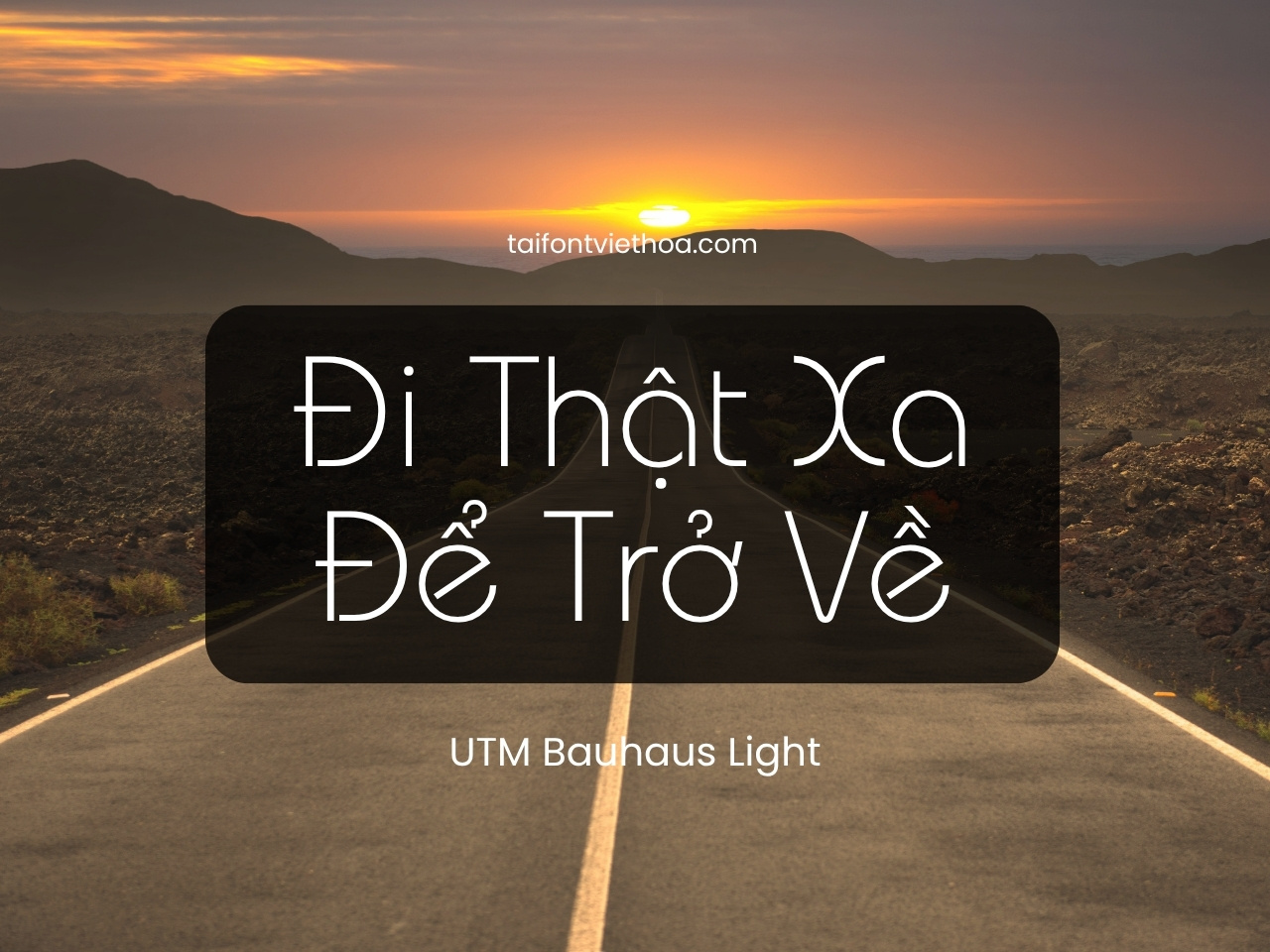
Font việt hóa UTM Bauhaus Light
Giới thiệu về font UTM Bauhaus Light
UTM Bauhaus Light là phiên bản Việt hóa của font Bauhaus Light – một kiểu chữ sans-serif hiện đại, lấy cảm hứng từ phong cách thiết kế Bauhaus nổi tiếng thế kỷ 20. Font gốc nổi bật với các nét chữ thanh mảnh, hình học đơn giản và thiết kế tối giản, mang lại sự tinh tế và hiện đại cho các dự án thiết kế kỹ thuật số và in ấn. Phiên bản Việt hóa đã được hoàn thiện để hỗ trợ đầy đủ tiếng Việt cùng hơn 200 ngôn ngữ khác, giúp mở rộng khả năng sử dụng trong các dự án sáng tạo đa dạng.
Đặc điểm thiết kế và ứng dụng của UTM Bauhaus Light
UTM Bauhaus Light sở hữu cấu trúc sans-serif không chân, với các nét chữ thanh mảnh, hình học rõ ràng và tỷ lệ cân đối. Font có độ dày nhẹ, phù hợp cho các thiết kế cần sự nhẹ nhàng và tinh tế, giúp tăng khả năng đọc trên nhiều kích thước và môi trường hiển thị. Font thích hợp cho các tiêu đề, nội dung văn bản và thiết kế nhận diện thương hiệu hiện đại.
Font phù hợp sử dụng trong thiết kế website, brochure, poster, logo và các dự án truyền thông đa phương tiện. Các ngành nghề phù hợp gồm: công nghệ, giáo dục, quảng cáo, thời trang và thương mại điện tử.